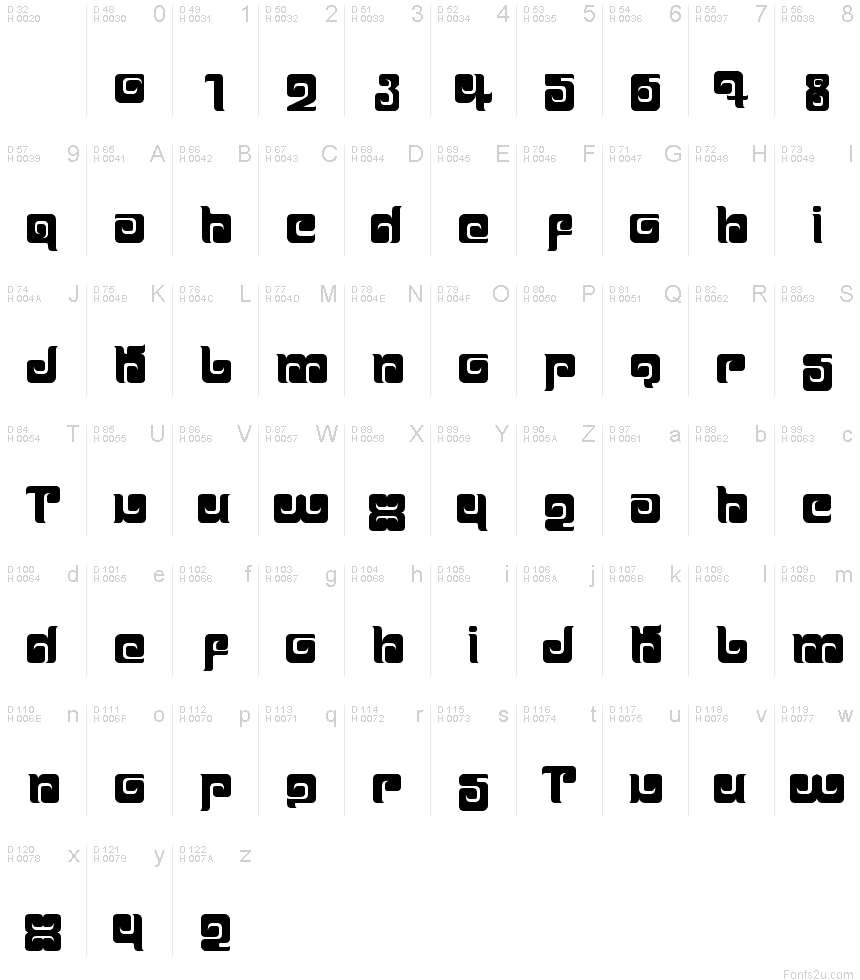
BALLOM autorstwa Marcio Hirosse to darmowy, groovowy krój typu display, który zamienia każde słowo w gruby, neonowy szyld. Jego masywne, blokowe kształty zakrzywiają się na rogach jak nadmuchiwane rurki, a puste wnętrza tworzą odważny, labiryntowy rytm, który sprawia wrażenie jednocześnie retro i futurystycznego. Ciasny odstęp sprawia, że litery łączą się w ciągłą, kolorową wstęgę – idealną, gdy chcesz, aby Twój nagłówek wyglądał jak jeden, spójny obiekt graficzny.
Dzięki BALLOM nadasz plakatom muzycznym, ulotkom imprezowym, brandingowi klubowemu, logotypom streetwearowym, opakowaniom czy grafikom do mediów społecznościowych natychmiastowy klimat łączący estetykę lat 70. z technologią. Ten darmowy font świetnie sprawdza się w dużych rozmiarach, gdzie miękkie krawędzie i wewnętrzne wycięcia pozostają wyraźne i czytelne. W przypadku dłuższego tekstu pomocniczego zestaw go z czystym, geometrycznym krojem bezszeryfowym i pozwól BALLOM przejąć rolę przykuwającego uwagę akcentu.
Zaprojektowane przez Marcio Hirosse